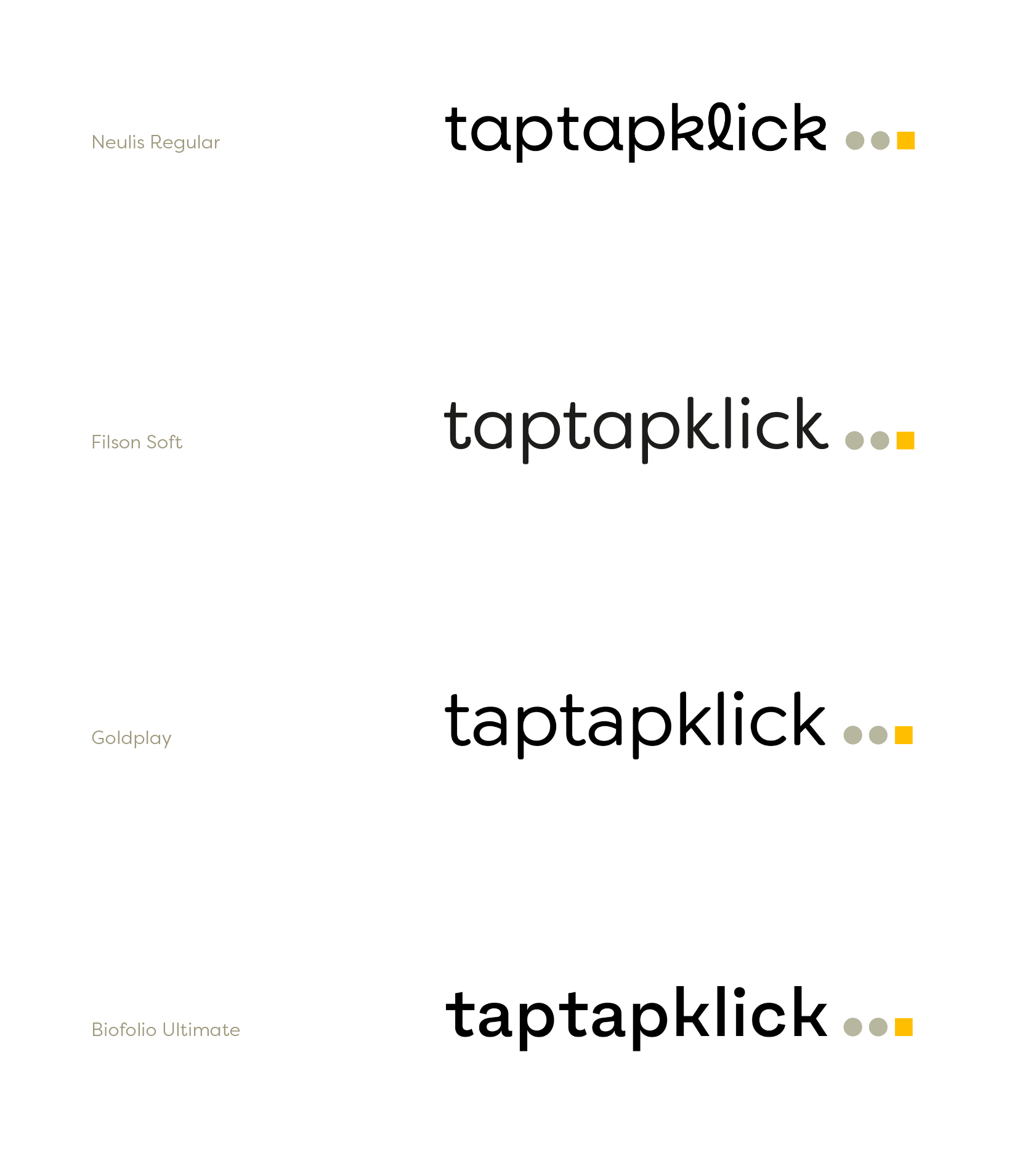
Suche Fonts ähnlich Filson Soft
für die Logoentwicklung eines privaten Projekts suche ich noch nach einer passenden Schriftart.
Ganz grob, ich mag öffentlich noch nicht zu sehr damit ins Detail gehen, geht es um Digitale Bildung für Kinder.
Grundsätzlich soll die Schrift ein modernes Erscheinungsbild habe, ohne stark ausgeprägte Serifen, ganz seifenlos muss es aber nicht sein. Von der Richtung her finde ich die Filson Soft schon nicht verkehrt.
Speziell die Kombination aus leicht weichen/abgerundeten Formen, gemischt mit einigen Spitzen, Ecken und klaren Formen empfinde ich als passend.
Gerne dürfen einige Buchstaben auch einen kleinen "Kniff" haben. Also wie bei der Filson z.B. der kleine Aufschwung rechts unten am "k".
Ich freue mich auf einige Anregungen. Die Schriften dürfen natürlich auch kostenpflichtig sein!
Wer ist die primäre Zielgruppe des Logos? Erwachsene oder Kinder?
Wenn Erwachsene, Eltern oder Professionelle?
Logo meint eine Wortmarke oder eine Graphik entweder mit oder ohne Wortmarke?
Hej! 🙂 Da gibt es mittlerweile so viel am Markt, dass eine deutlichere Eingrenzung wohl wirklich ganz hilfreich wäre:
1. Etwas Humanistisches wie die Milo?
2. Eine eher Statische wie die Andes?
3. Oder eine Geometrische Sans wie die Isidora oder eben Filson?
Und gerundete Strichenden (siehe Filson und verlinkte Isidora Soft) oder nicht?
Ja, es ist noch recht vage. Es ist ein erster Schritt.
Zielgruppe sind ganz klar Erwachsene, keine Kinder.
Eltern bzw. Professionelle ist nicht ganz trennscharf. Es wird sicherlich auch Eltern geben, die das aus Interesse lesen, aber Fokus der Zielgruppe  wird mehr bei Lehrern, Designern und Front-End-Entwicklern liegen.
Das Logo wird eine Wort-Bild/Marke.
Im Anhang einmal der aktuelle Stand. Es wird da noch Anpassungen im Detail geben, das Grundprinzip der zwei Kreise und dem Quadrat bleibt bestehen. Daher auch die Idee, in der Typo die runde (weiche) als auch die harte (kantige) Form aufzugreifen.
Humanistisch fällt raus. Sowohl die Andes als auch die Isidor gefallen auf Anhieb schon einmal gut.
Eher Richtung statisch als geometrisch.
Wobei ja bei dem derzeitig streng geometrischen Bildmarken-Ansatz eine Geometrische Sans sehr sehr nahe läge. ;-)
Kannst Du die Frage nach den runden Strichenden noch beantworten?
Daher auch "eher" statisch. Ich bin dem anderen nicht abgeneigt.
Ich muss mir erst einmal selber einen Überblick verschaffen.
Nach meinem Berufswechsel vor einigen bin ich aus der Typo ziemlich raus.
Ist ja aber auch nur ein privates Projekt. Da gibts keine schimpfenden Kunden. 🙂
Bei den Strichenden bin ich auch noch unentschlossen. Kommt mir aufs Gesamtbild an.
Spontan aus dem Bauch raus: Tendenz runde Strichenden, da die Bildmarke rechts der Typo steht und dann gefälliger übergeht. Andererseits könnte auch der Ansatz Spannung erzeugen, die runden Punkte beiderseits mit kantigen Formen einzurahmen.
Das hilft nun vermutlich nur bedingt weiter. 🙂
Daher auch "eher" statisch.
Jetzt bin ich verwirrt.
Kommt mir aufs Gesamtbild an.
Spontan aus dem Bauch raus: Tendenz runde Strichenden, da die Bildmarke rechts der Typo steht und dann gefälliger übergeht.
Du könntest ja auch dem Rechteck ein paar dezente Abrundungen (Eckradius evtl. sogar abgeleitet vom Font) verpassen.
Hier mal noch ein paar leicht verspielte Geometrische, welche ich zum derzeitigen Stand der Bildmarke und das beschriebene Projekt recht passend fände:
• Epillox
• Neulis
• Biofolio
An die Isidora (ohne abgerundete Strichenden) kommt man momentan bei designcuts sehr günstig ran, vorrausgesetzt deren Lizenz passt zu Deinem Projekt.
vor 17 Minuten schrieb El Vulpes:
Zielgruppe
Ich bin kein Designer, stelle aber mal meine Gedankengänge zur Verfügung:
Ausgehend von der Zielgruppe sind Eltern raus und Lehrer*innen kann man mehrheitlich ignorieren, da diese alles toll finden, was nicht nicht aussieht als ob eine Schweineherde über eine polierte Marmorplatte gerannt ist (letzteres ist eine gesunde Mischung aus Erfahrung und Vorurteil 😄). Bleiben also die Designer*innen und Front-End-Entwickler*innen. Erstere können quasi alles ansprechend finden, sofern es irgendwie schön und/oder gut (diese καλοκἀγαθία hilft auch bei Lehrer*innen) ist. Bleiben also die Entwickler*innen. Da diese oft mit viel Code zu tun haben, liegt hier eine Schrift für mich nahe, die dieses auch aufgreift.
Deswegen werfe ich mal fernab der der bisherigen Vorschläge die Recursive ins Rennen, die in ihrer Variabilität (scnr) auch anderswo noch Verwendung finden könnte.
vor 2 Minuten schrieb Phoibos:
Bleiben also die Entwickler*innen. Da diese oft mit viel Code zu tun haben, liegt hier eine Schrift für mich nahe, die dieses auch aufgreift.
Das Tappen ist dabei für mich eher ein sanftes, weiches rundes Geräusch, das Klicken mehr was spitzeres, kantiges und höheres. Daher die beiden Formen, die auch so erhalten bleiben sollten.
Mir gefällt diese Lösung ganz gut, weil da der Klick als quasi Ergebnis des Tappens 'rüberkommt. In der Richtung würde ich weitermachen.